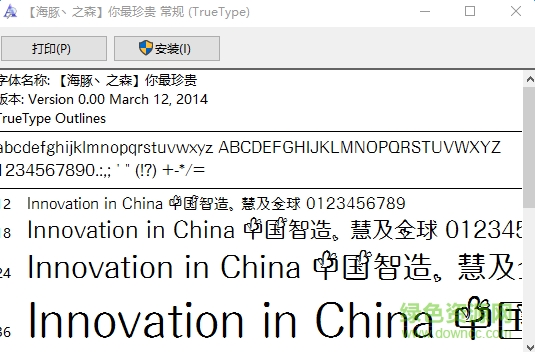
你最珍貴字體是一款很不錯(cuò)的電腦個(gè)性字體,這款字體也正是因?yàn)樗莫?dú)特之處而深受廣大朋友們的喜歡,不管是藝術(shù)設(shè)計(jì)、廣告設(shè)計(jì)還是在書(shū)畫(huà)上面題字題詞都是很不錯(cuò)的,喜歡的朋友可以來(lái)綠色資源網(wǎng)下載。